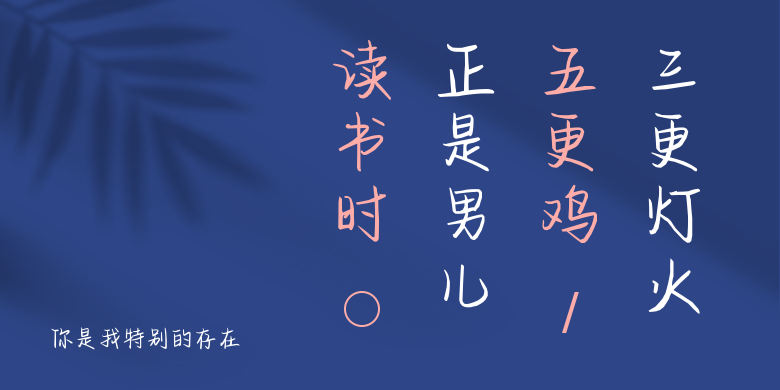
你是我特别的存在
你是我特别的存在,这款字体结构工整、笔画清晰,兼顾美观与易读性,适用于标题、正文、海报、包装、LOGO 等多种场景。字形优雅稳定,风格百搭耐看,适配日常排版与创意设计,让文字呈现更舒适、更具质感。你是我特别的存在一笔一画,皆是细节,以均衡的比例、流畅的线条打造舒适视觉体验,字形端正大气,风格简约现代。无论是商业设计、品牌宣传还是日常排版,都能轻松驾驭,让文字更有格调与力量。你是我特别的存在字体下载。